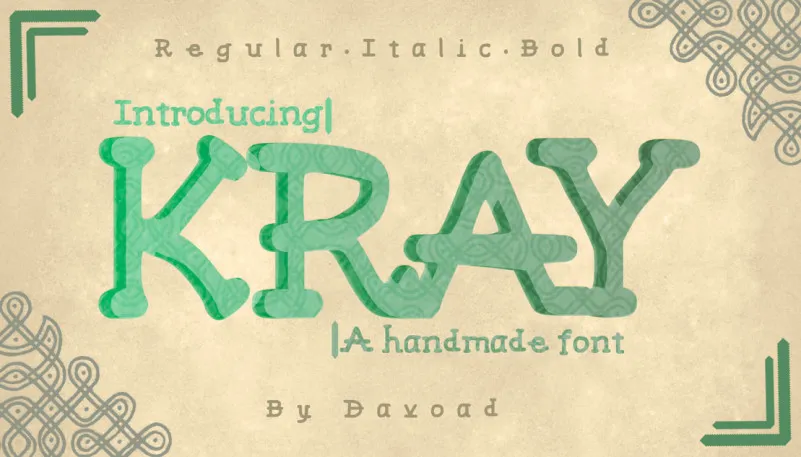
Kray Typeface – Fonte Grátis
Kray Typeface
A Kray Typeface é uma fonte playfull criada pelo designer Davoad que se destaca por sua alegria e diversão. Seu estilo desenfreado, com traços livres e interessantes, está repleto de personalidade para adicionar um toque único aos seus projetos digitais. Perfeita para trabalhos como logos, gráficos publicitários ou designs web, esta fonte vai fazer você se divertir enquanto adiciona uma vibe descontraída a sua marca. Combinar diferentes estilos e traços da Kray Typeface pode criar um resultado incrível, tornando-a perfeitamente adaptável para qualquer aplicação visual. Seja para criar um design moderno ou um artesanato personalizado, esta fonte vai encantar os olhos do usuário.